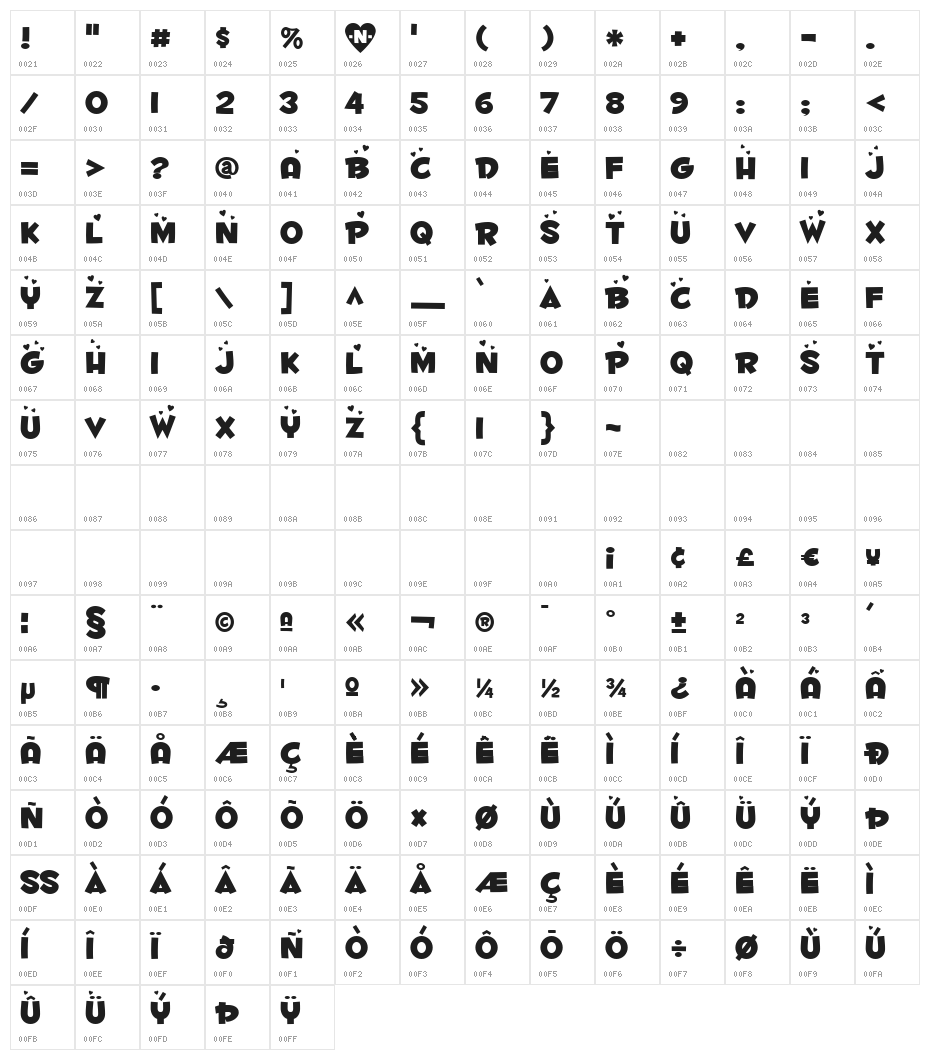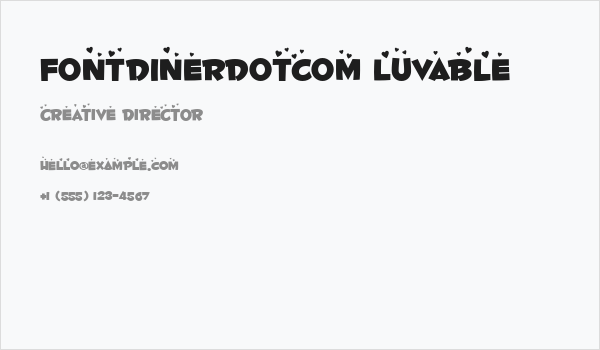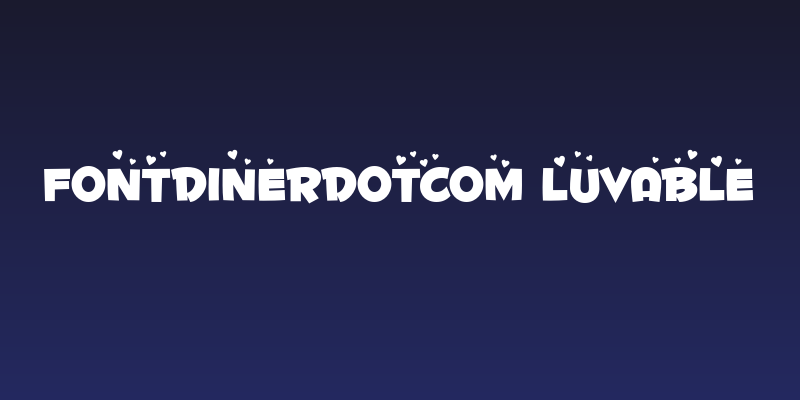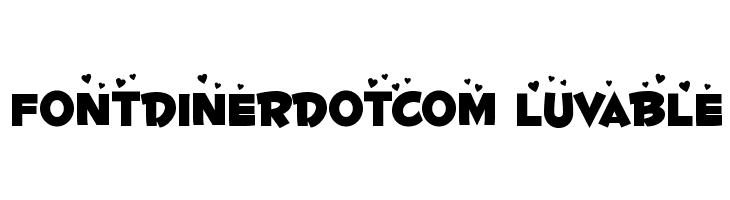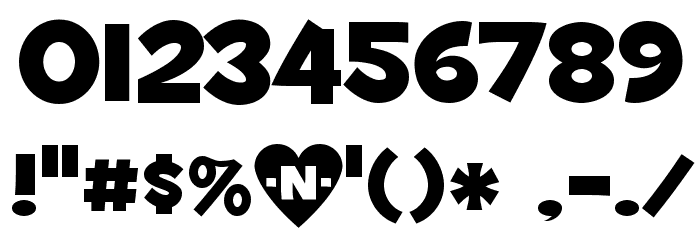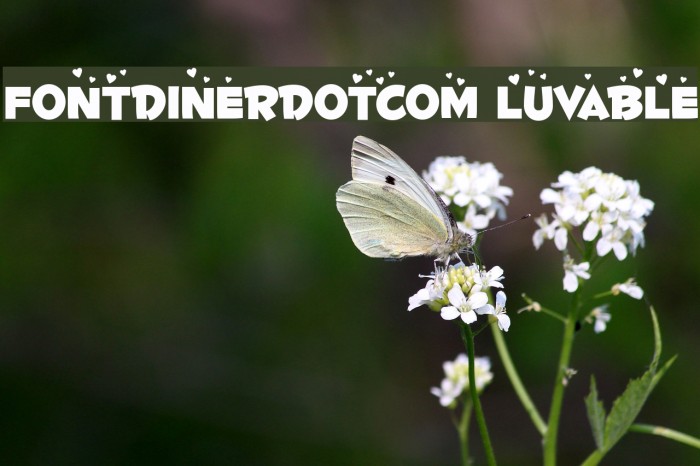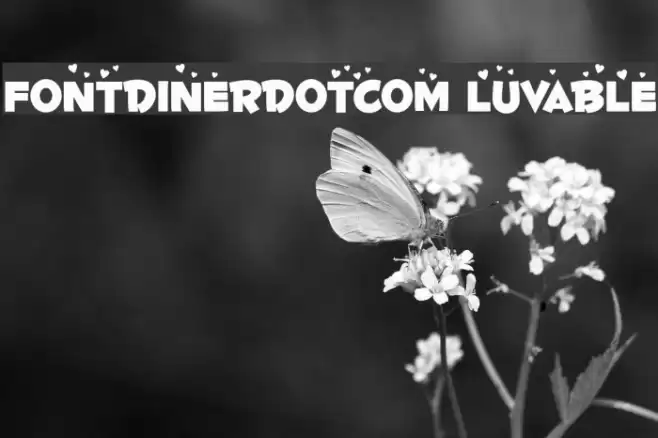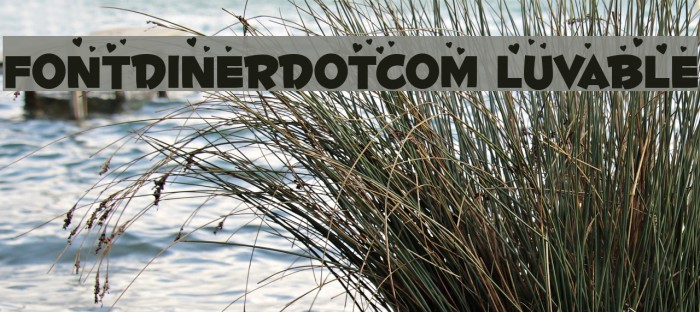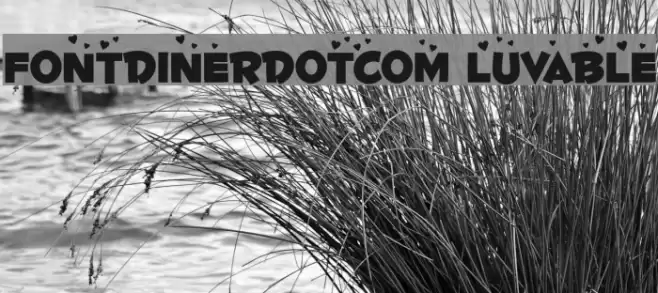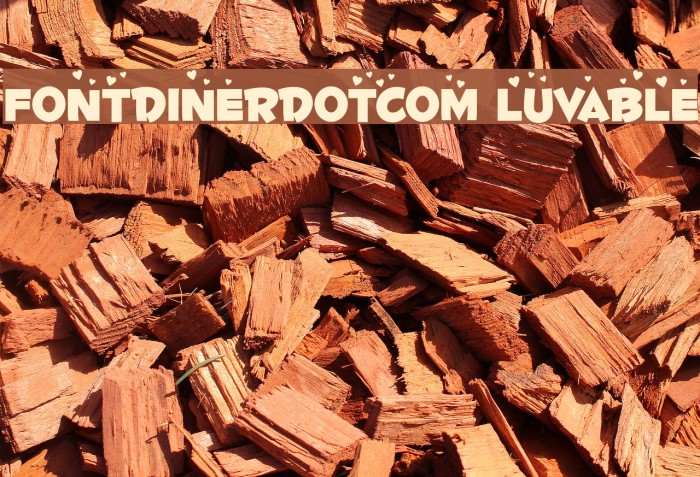
Fontdinerdotcom Luvable Font
| 用途 | Logos, Headlines, Invitations |
| おすすめプロジェクト | Perfect for Valentine's Day cards, wedding invitations, playful branding, children's books, and any design needing a touch of whimsy and love. |